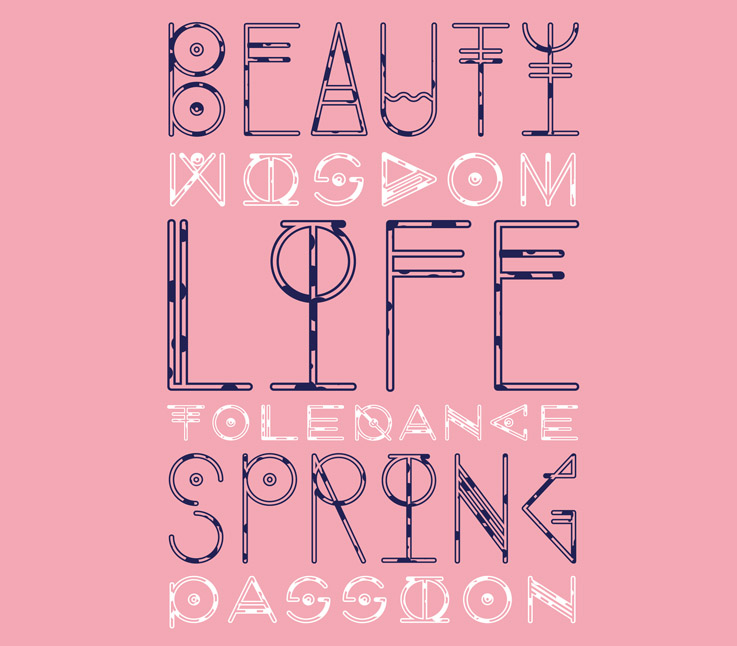
Lo que en un primer momento se pensó como un encargo para la banda mexicana Mana, acabó siendo una fuente tipográfica experimental con el nombre de Mana Endemic.
Eventhough at first this project was thought as a commission for the Mexican band Mana, ended up being an experimental typeface with the name of Mana Endemic.